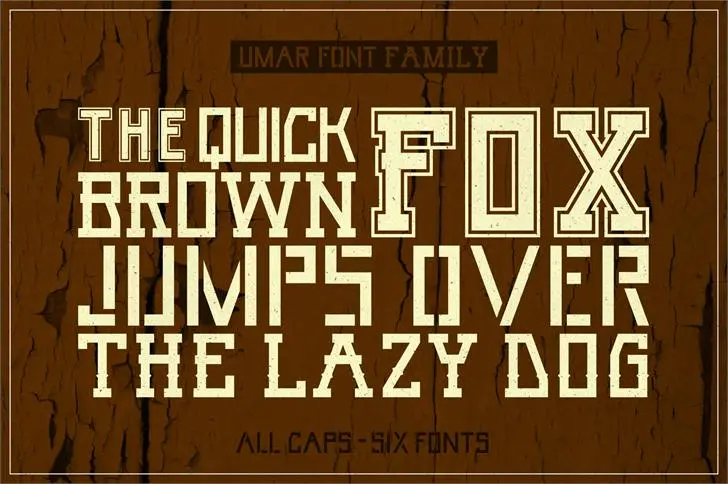
A Umar Font Family é uma elegante família serif que oferece uma gama completa de características para designers de gráficos. Desenvolvida pelo talentoso designer Hamilton, a Umar traz consigo um estilo firme e sofisticado capaz de dar vida às mais variadas criações digitais. Suas linhas leves e bem definidas proporcionam um visual profissional e moderno que se destaca em qualquer projeto. Com múltiplas opções de tipo, incluindo itálico, negrito e alternativas, a Umar é perfeita para quem busca um estilo elegante para seus materiais digitais. Seja para websites, logotipos ou publicações impressas, a Umar atende as necessidades dos designers em busca de uma fonte serif versátil e poderosa.